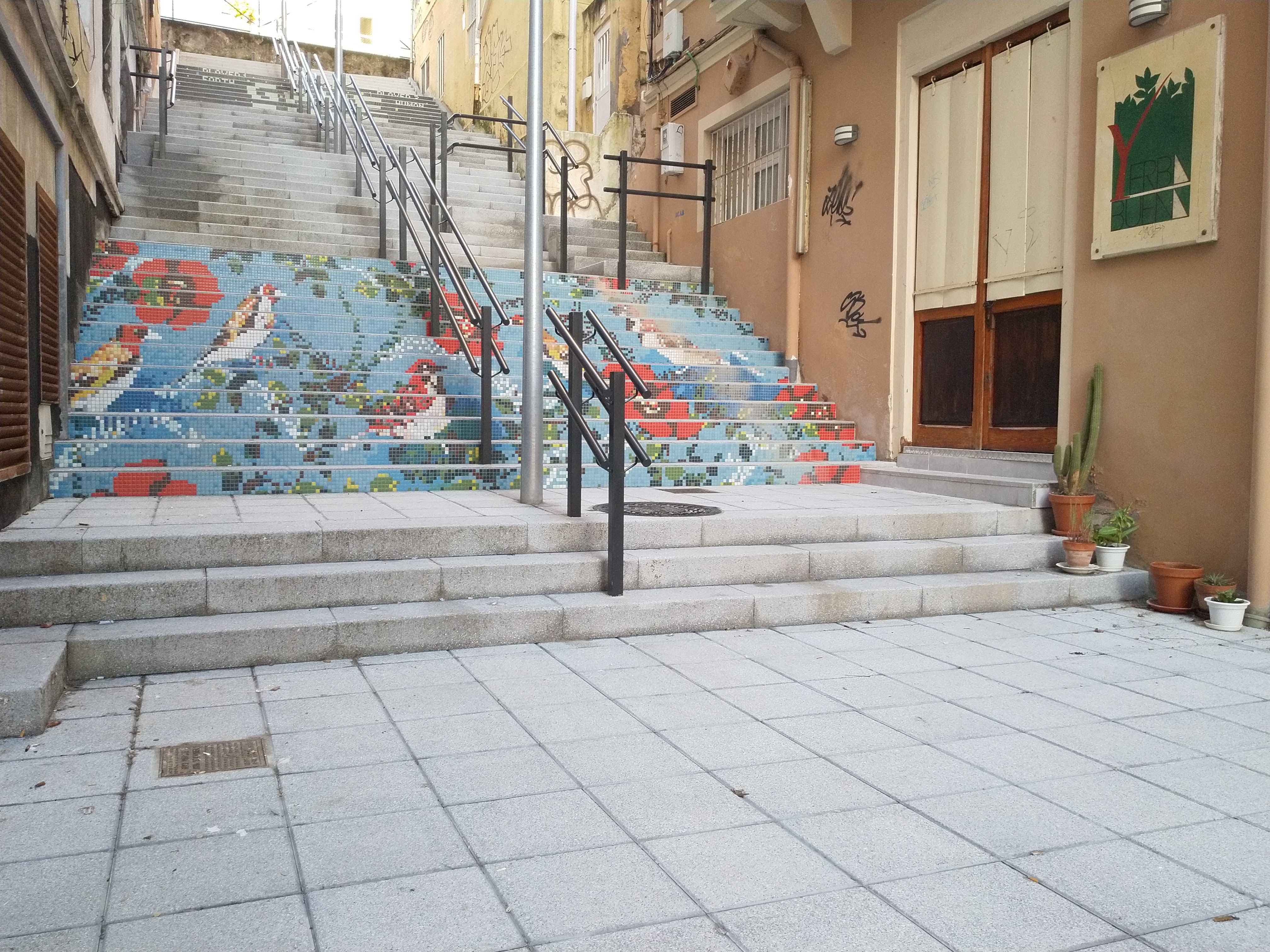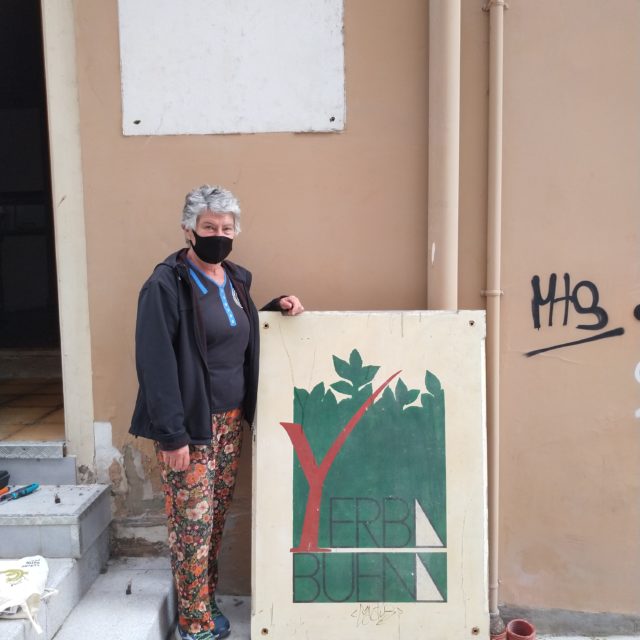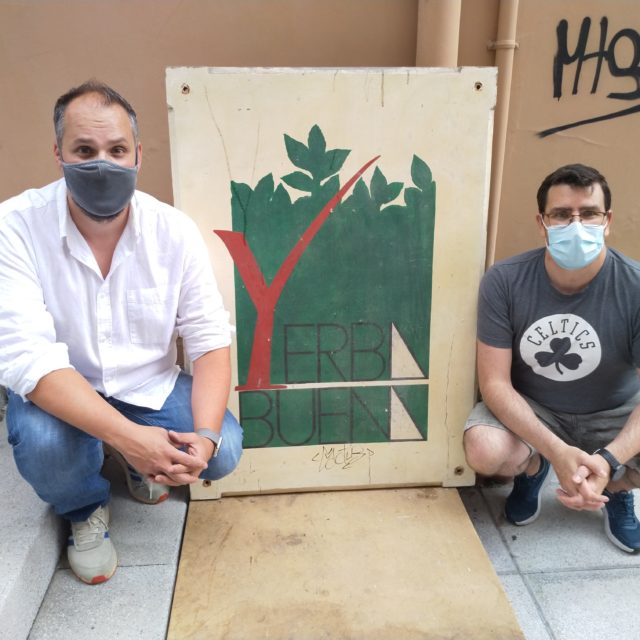
Restaurante Yerbabuena
El Restaurante Yerbabuena fue fundado en 1987 por 4 socios tras venir de “La Paquita”, uno de los locales más reconocidos culturalmente en el Río de la Pila, con su icónica Bolera.
Desde su origen un local con una gran actividad cultural, donde se podía comer, escuchar conciertos, recitales, exposiciones, teatro, etc. Nos decía “Chuska” que por aquí pasó un desconocido Marcos Bárcena. Pero no sólo en lo cultural, el “Yerbabuena” también fue un restaurante comprometido, que acogió a organizaciones y entidades comprometidas socialmente en sus salones. Con todo ello el Yerbabuena fue un epicentro cultural y social. Tras más de treinta años de actividad, cierra por jubilación de “Chuska” en noviembre 2020.
El cartel de madera y la imagen, fue creado por el diseñador gráfico y artista Carlos Limorti (Santander, 1956) con ese Yerbuena con “Y” en un guiño al sur.